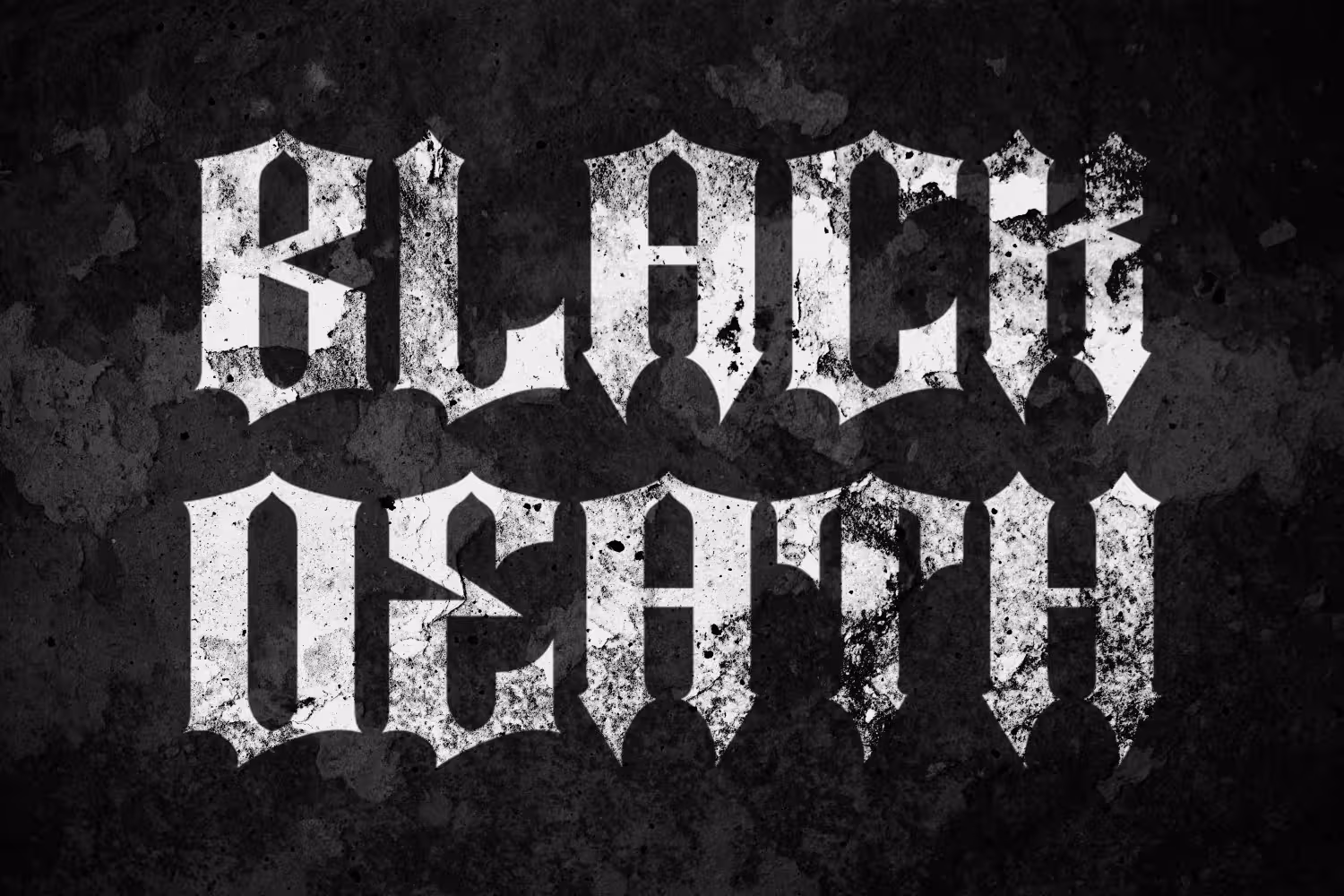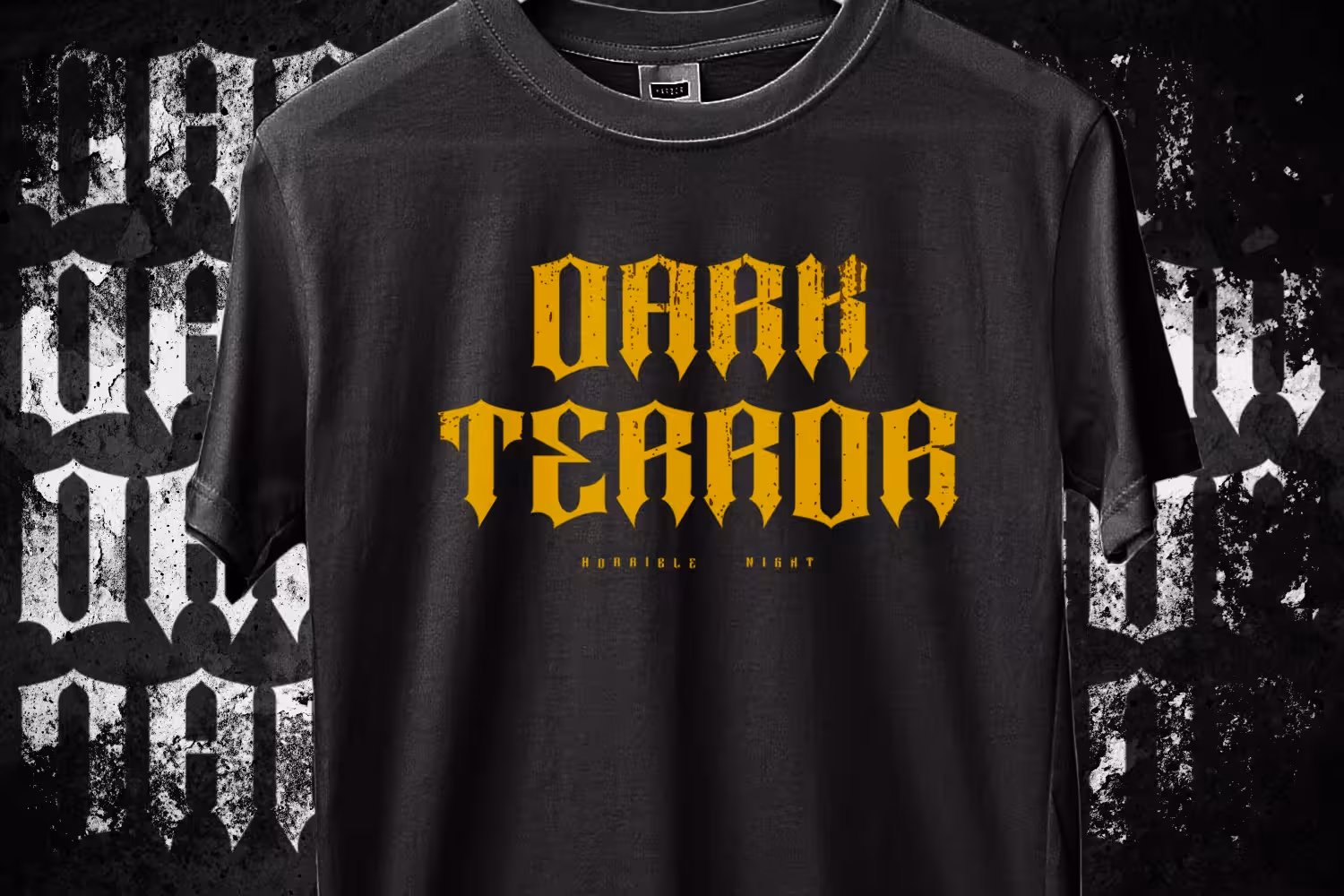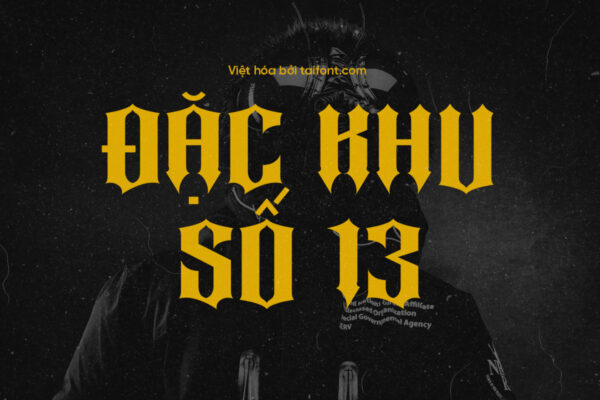
Giới thiệu về Font TF Gorilla Monster Việt hóa
TF Gorilla Monster Việt hóa là một font chữ nổi bật với thiết kế độc đáo, mạnh mẽ và đầy cá tính, lý tưởng để truyền tải sự hoang dã, dữ tợn và đầy kịch tính. Font này toát lên phong thái hung tợn, bí ẩn và có chút rùng rợn, rất phù hợp với các thiết kế mang tính hành động, kinh dị hoặc phiêu lưu.
Với đặc điểm thiết kế mạnh mẽ và khả năng gợi cảm xúc mạnh, Gorilla Monster là lựa chọn lý tưởng cho các ấn phẩm trong lĩnh vực game và điện ảnh:
- Poster game: Hoàn hảo để sử dụng cho poster quảng bá các tựa game hành động, nhập vai, chiến thuật hoặc game kinh dị. Font này giúp tạo không khí kịch tính, lôi cuốn và đầy thử thách, khiến game thủ cảm thấy hào hứng.
- Poster kinh dị: Lý tưởng cho poster phim kinh dị, bìa sách truyện ma, hoặc các ấn phẩm liên quan đến chủ đề bí ẩn, rùng rợn. Gorilla Monster giúp truyền tải sự căng thẳng, bí ẩn và cảm giác sợ hãi một cách hiệu quả, thu hút những người yêu thích thể loại này.
- Thiết kế thương hiệu (độc đáo): Phù hợp cho các thương hiệu muốn thể hiện sự mạnh mẽ, độc đáo và một chút “chất” riêng biệt.
Với TF Gorilla Monster Việt hóa, bạn có thể dễ dàng thổi hồn mạnh mẽ, sự bí ẩn và sự độc đáo vào các thiết kế, tạo ra những sản phẩm không chỉ đẹp mắt mà còn đầy cảm xúc và câu chuyện.